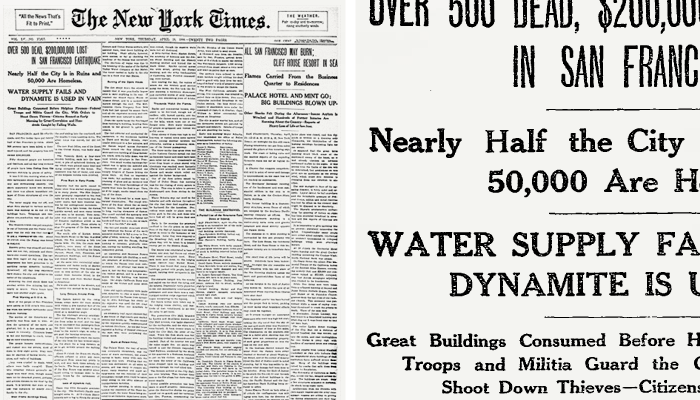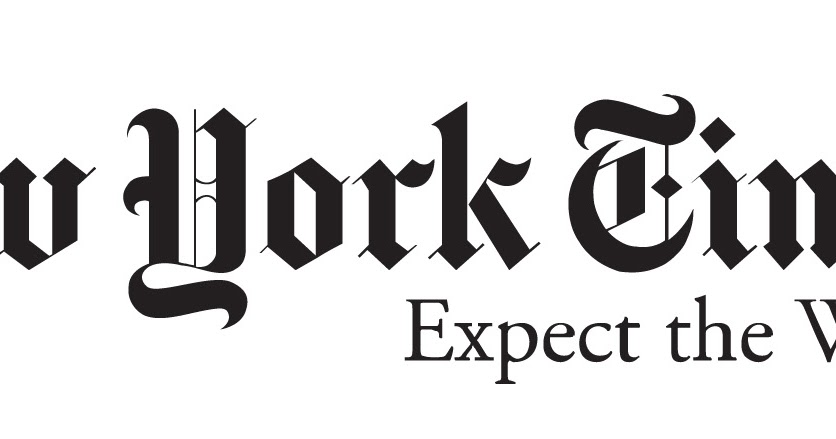
Дизайнер участвовал во Второй мировой войне, играл на барабанах, был на грани банкротства и за карьеру создал и «возродил» более 600 шрифтов.
Типограф Эд Бенгуиат, 2020 год Type Directors Club
Играл с инструментами отца, увлекался музыкой
Типограф и дизайнер Эд Бенгуиат родился в 1927 году в Бруклине. Его мать работала водителем в Красном Кресте, а отец — арт-директором в сети универмагов Bloomingdales.
Мальчик играл с отцовскими кистями, ручками и чертёжными инструментами, а также увлекался музыкой — на десятилетие папа подарил ему барабанную установку.
Эд Бенгуиат, 1928 год SVA Archives
После школы он ушёл на фронт Второй мировой войны. Поначалу Бенгуиата не брали в армию, так как ему не исполнилось 18 лет. Спустя годы дизайнер признался, что на службу помог попасть отец, который подделал документы, изменив дату рождения и фотографию сына.
Бенгуиат поступил на службу в военно-воздушные силы армии США. В 1944–1945 годах он был пилотом истребителя-бомбардировщика и занимался фоторазведкой над оккупированной Европой.
По рассказам дизайнера, летать было опасно: все портовые верфи и железнодорожные депо вооружались зенитной артиллерией. Даже в поездах стояли орудия, военные охраняли мосты.
Я искал поезд, затем летел вперёд и находил участок пути с большим поворотом или туннелем. Дозорные и инженеры не видели, что находится за поворотом.
Незадолго до того, как состав достигал этого участка, я взрывал пути.
Эд Бенгуиат
После службы в авиации у него сохранилось увлечение самолётами. В 1980-х годах Бенгуиат самостоятельно пилотировал и состоял в аэроклубе The Flying Birdmen.
Бенгуиат на аэродроме Print Magazine
Днём — дизайн и каллиграфия, вечером — джаз
После войны мужчина вернулся к ударным инструментам и получил степень бакалавра музыки в Бруклинском колледже.
Он играл в джазовых группах под именем Эдди Бенарт. Выступал в клубах и на концертах, в том числе в коллективах с кларнетистом Вуди Германом и пианистом Стэном Кентоном.
В конце 1940-х годов музыкальный журнал Metronome опросил читателей и поставил будущего дизайнера на третье место среди лучших барабанщиков Америки.
Однажды он пошёл платить взносы в профсоюз музыкантов и увидел стариков, которые играли на праздниках и свадьбах. Он подумал, что не хочет стать таким же бедным пожилым музыкантом. И тогда надпись «будь художником» в заведении возле клуба, где играл барабанщик, вдохновила пойти в иллюстраторы.
Я хочу стать художником, буду рисовать дам, куплю красивый дом и стану известным, как Альберто Варгас или Джордж Петти.
Эд Бенгуиат, перед началом обучения дизайну
Благодаря льготам участника войны музыкант оплатил обучение в мастерской школы рекламного искусства. Он хотел писать обнажённую натуру, но, по мнению учителя живописи, будущий дизайнер не умел рисовать.
Педагог посоветовал ему уйти из искусства.
Типограф рассказал, что через 40 лет встретил этого учителя в школе визуальных искусств, подошёл к нему со словами: «Не знаю, помните ли вы, меня зовут Эд Бенгуиат…» Он собирался поговорить с преподавателем о прошлом, и тот ответил: «О, я знаю вас, я всё время пользуюсь вашими шрифтами».
После совета уйти из искусства Бенгуиат сменил направление. В школе он стал изучать дизайн и каллиграфию, там же проводили курсы по шрифтам, иллюстрации, живописи. Студент засиживался на занятиях больше десяти часов и исписывал целые листы буквами.
В 1950 году у него родился сын, и чтобы прокормить семью, Бенгуиату пришлось давать концерты по ночам. «Я играл джаз, приходил домой, работал над буквами и кормил ребёнка!» — вспоминал он.
Логотип для Esquire
В начале 1950-х Бенгуиат работал во многих агентствах и издательствах: в киножурналах Movie Magazines и Romance Magazines, ретушировал декольте на фотографиях в компании The Haze Office.
К 1953 году он стал заместителем директора Esquire. В издании дизайнеру дали одну из первых задач — изменить старый логотип, чтобы журнал выделялся среди других газет.
Логотип Esquire до дизайна Бенгуиата Flickr
Бенгуиат постарался сохранить оригинальный знак узнаваемым, сделал его более сплющенным и массивным за счёт утолщения букв и расширения логотипа по горизонтали.
Логотип Esquire после дизайна Бенгуиата Flickr
Открыл свою студию и оказался на грани разорения
В том же 1953 году Бенгуиат открыл студию дизайна Associates Benguiat and Co и нанял 21-го сотрудника.
Одним из первых клиентов стала фармкомпания Schering Pharmaceuticals — она попросила сделать карты штатов США с названиями медицинских университетов. Чтобы сэкономить, студия решила не нанимать специалиста по каллиграфии, Бенгуиат сам создал дизайн букв и позже продал его одной из старейших типографий Photo-Lettering.
После этого та предложила дизайнеру несколько других проектов, в том числе шрифт для Ford.
Также у Associates Benguiat and Co появились два крупных заказчика — электротехнические компании Westinghouse и General Electric. На последнюю Бенгуиат вышел благодаря «тайному» арт-директору агентства-посредника.